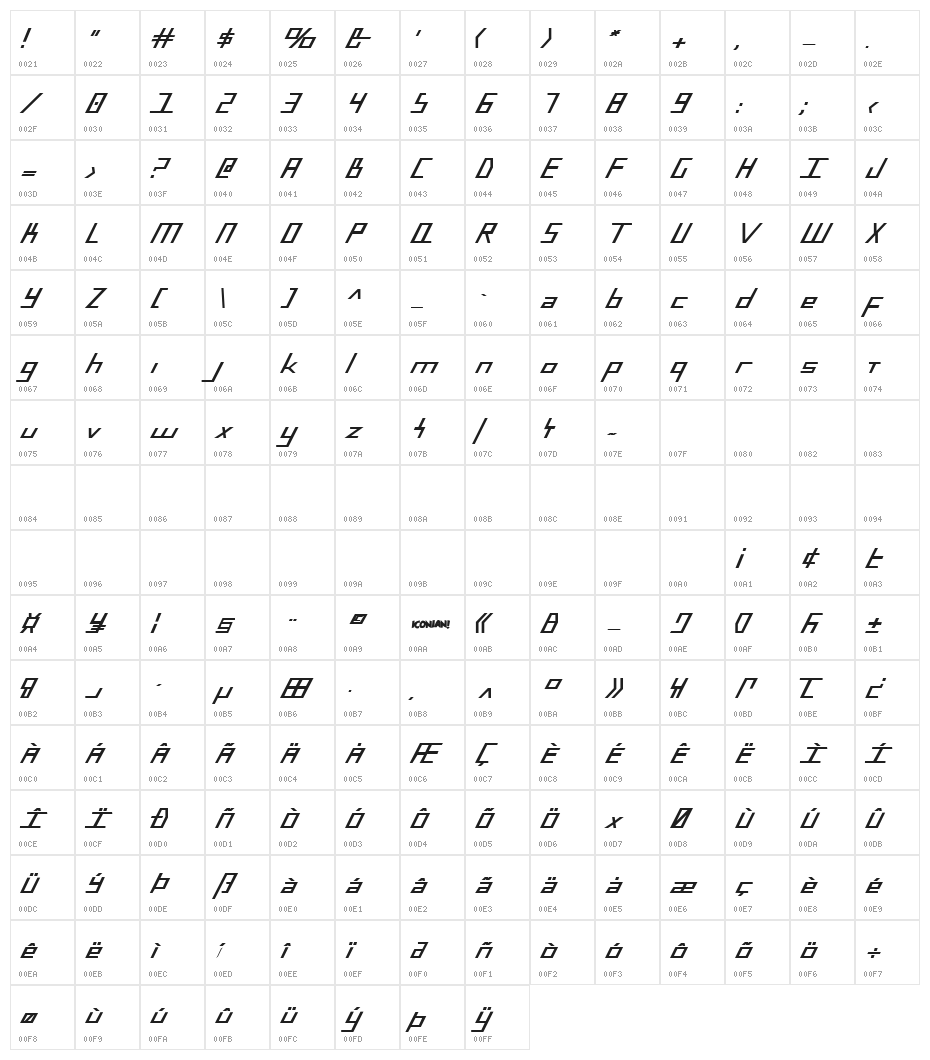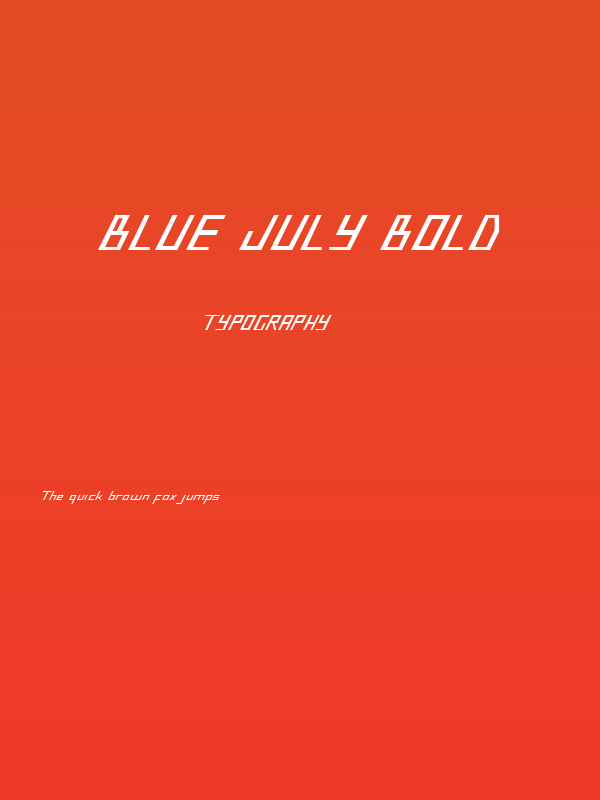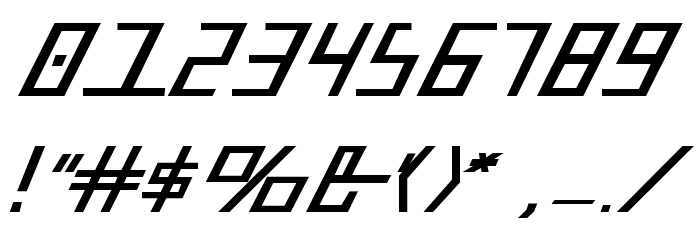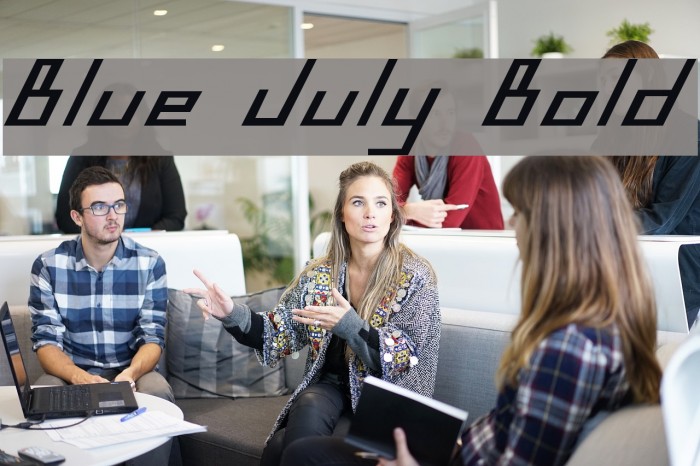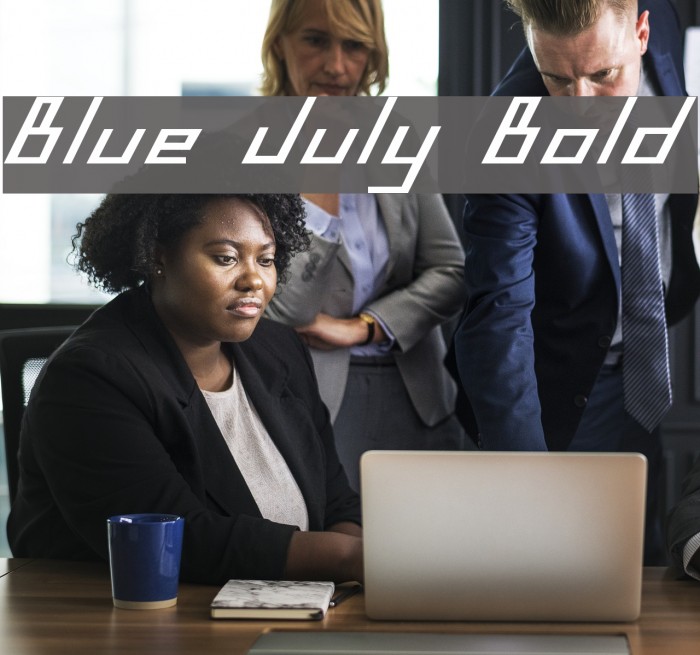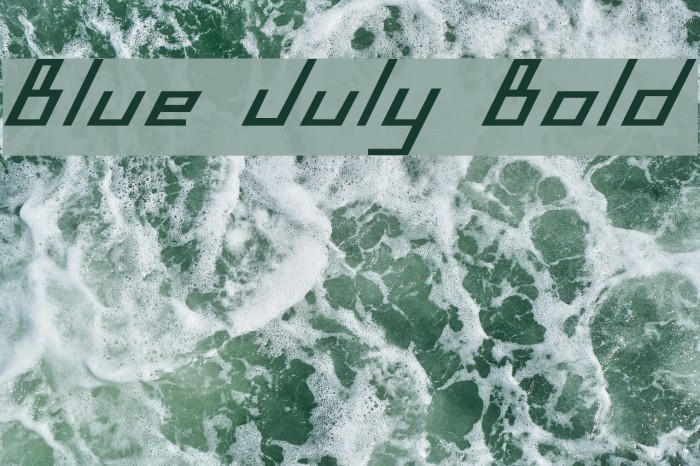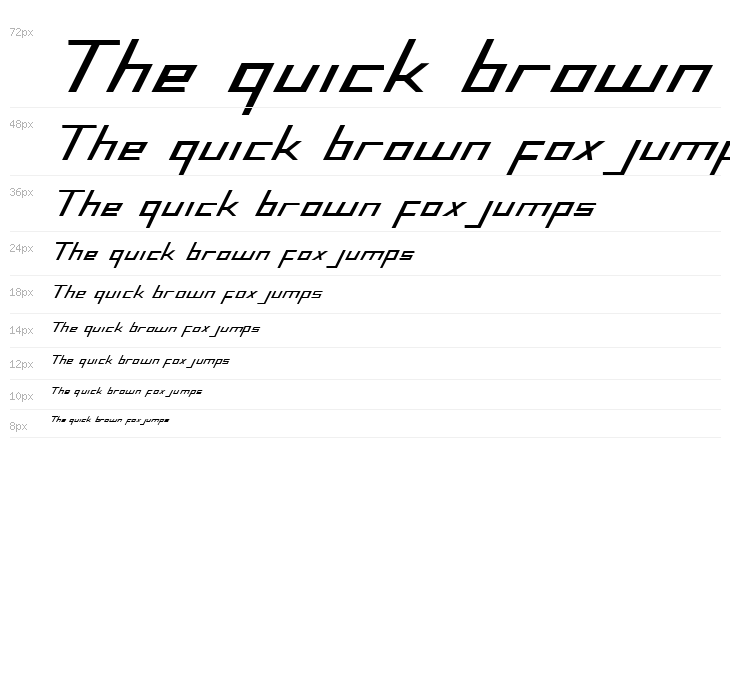
Blue July Bold Font
| Poids | Bold |
| Cas d'utilisation | Headlines, Logos, Branding |
| Projets proposés | Ideal for branding, advertising, and digital media projects that seek a modern and edgy look. |
Blue July Bold